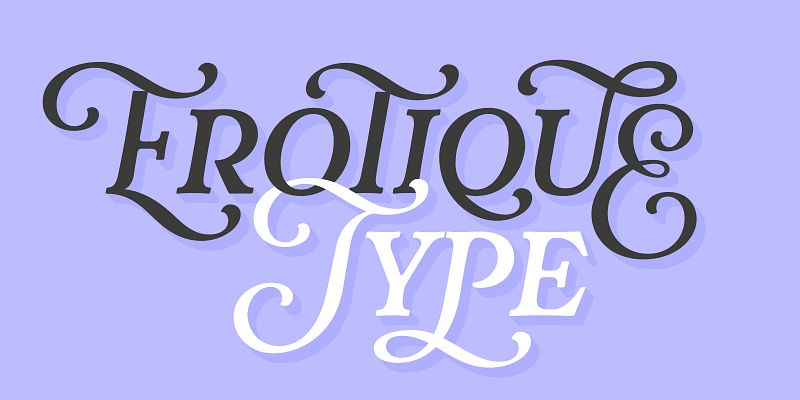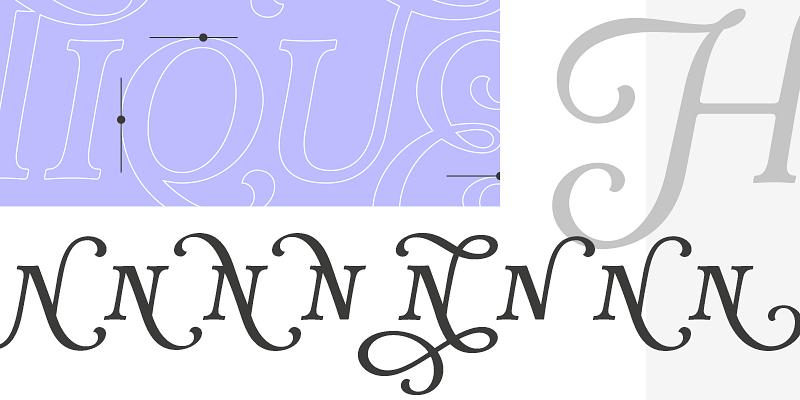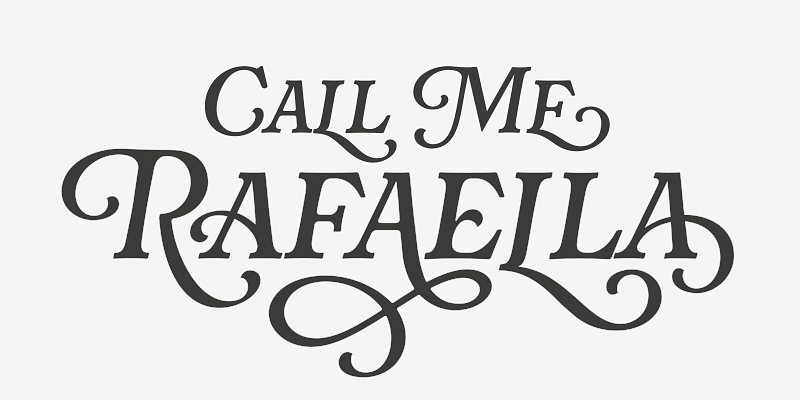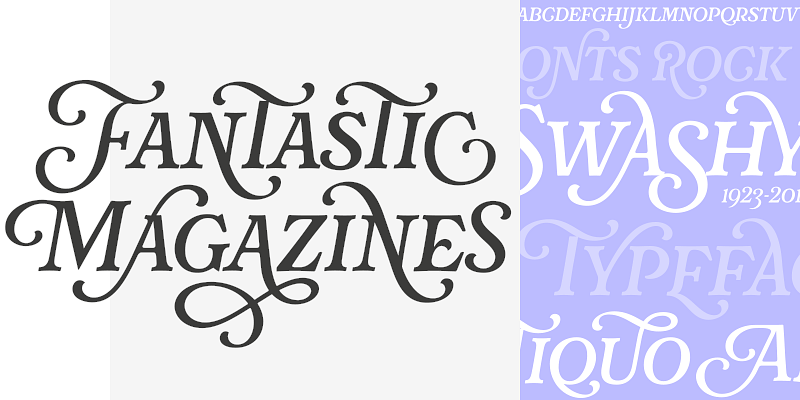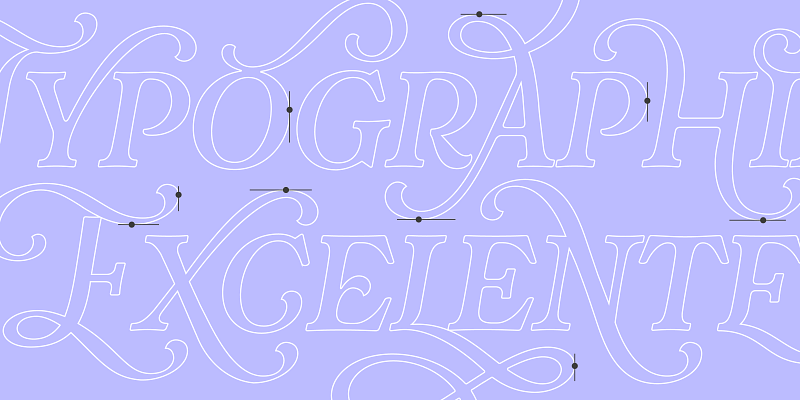
Sproviero Type ha creado un catálogo galardonado de fuentes bien trabajadas, atractivas y modernas, sin dejar ningún detalle fuera. El diseñador tipográfico Maximiliano Sproviero poner a trabajar su pasión por la caligrafía y las letras con una sorprendente colección de tipos de letra únicas fantásticamente decoradas, imaginativamente adornadas y sorprendentemente originales. Cualquiera que sea el producto o medio, las fuentes de Sproviero Type crean el ambiente para que tus reflexiones e ideas se transformen en realidad.